Как различить 0, 3, 6, 8 и 9 в рукописном шрифте
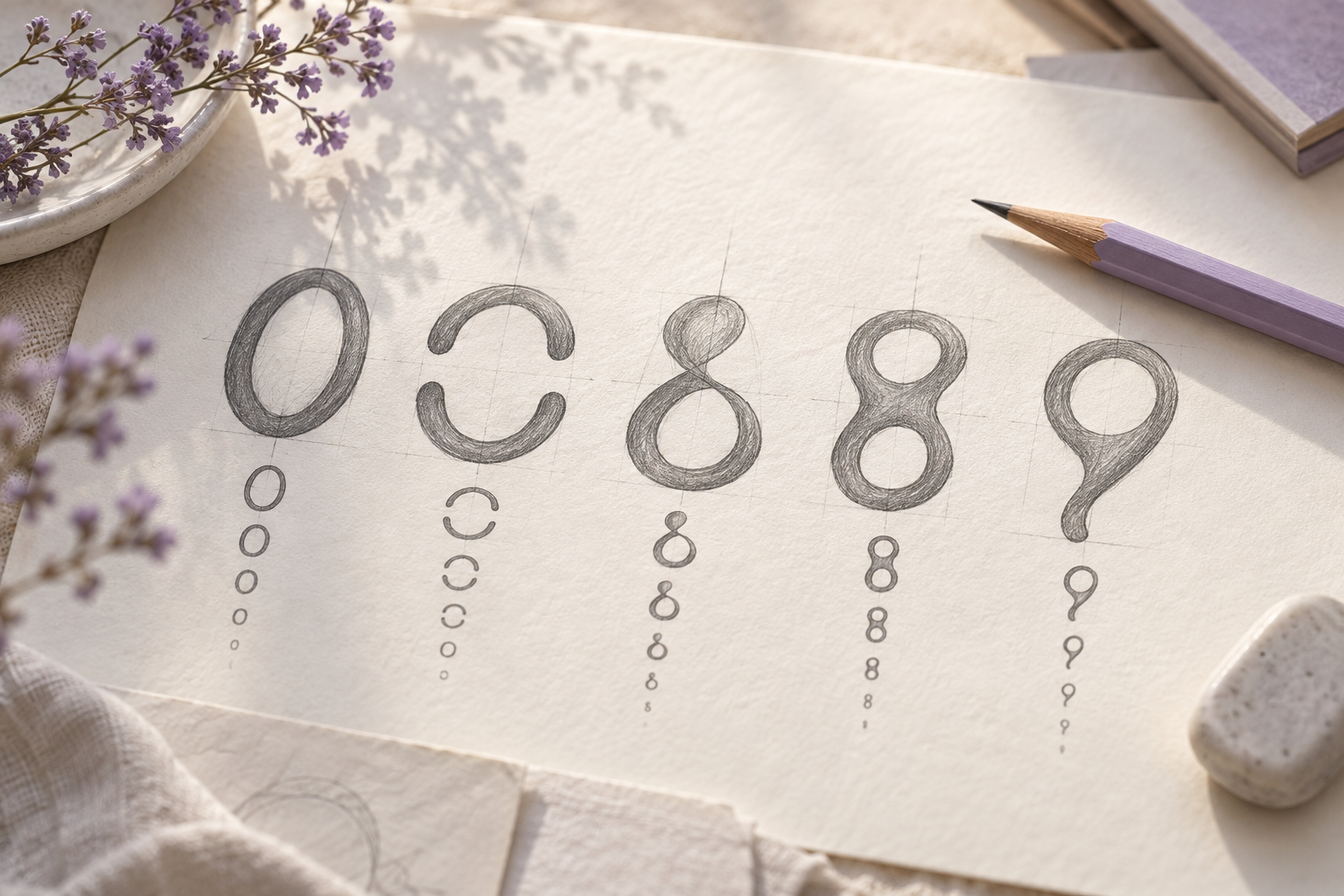
В рукописном шрифте цифры 0, 3, 6, 8 и 9 должны оставаться узнаваемыми не только по отдельности, но и в коротких числовых строках. Для этого каждой цифре задают собственный силуэт, распределяют массу штрихов и сохраняют просветы, которые не исчезают при уменьшении. Ниже — рабочий способ нарисовать спорную группу и проверить её в нужном размере.
Почему именно эти цифры начинают сливаться
В этой группе много округлых контуров и замкнутых или почти замкнутых просветов. У 0 есть одна полость, у 8 — две, у 6 и 9 — по одной, а 3 состоит из двух открытых чаш. Когда почерк превращают в шрифтовые знаки, стилизуют линию и уменьшают изображение, различия между этими конструкциями могут стать слабее: петля 6 закрывается, верх 9 теряет направление, а 3 выглядит как недорисованная 8.
Проблема обычно не в том, что отдельная цифра нарисована плохо. Нечитаемость возникает из-за отношений внутри набора: одинаковой ширины, похожего наклона, схожих соединений или чрезмерно мелких просветов. Поэтому полезно смотреть на группу целиком и сравнивать знаки попарно. Цель — не сделать пять цифр из разных гарнитур, а встроить их в один характерный почерк, оставив каждой устойчивый признак.
Сначала задайте общие правила набора
Перед деталями определите базовую конструкцию: общую высоту цифр, направление наклона, толщину основного штриха и характер округлений. В рукописном начертании линия может слегка колебаться, однако эти параметры должны быть последовательными. Если у 0 овальная вертикальная форма, остальные округлые знаки тоже могут быть немного вытянуты, но их ширина и пропорции не обязаны совпадать с нулём.
Задайте для каждого знака один главный отличительный жест. Ноль может быть узким и спокойным овалом; тройка — открытой справа, с заметно разными верхней и нижней чашами; шестёрка — с петлёй, которая явно возвращается к нижней части; восьмёрка — с двумя различимыми полостями; девятка — с верхней чашей и направленной вниз ножкой. Это не универсальный стандарт рисунка, а система решений, которую нужно согласовать с собственным стилем.
Полезно зафиксировать также минимальный внутренний просвет. Для округлых форм он часто оказывается важнее внешнего контура: слишком маленькая полость в 8 превращается в плотный узел, а узкое раскрытие в 3 теряется при масштабе. Не нужно выводить теоретическое число. Ориентируйтесь на конечное применение: размер ценника, подписи, интерфейсного значения или другого самого мелкого текста, где цифры должны читаться.
Разведите цифры по силуэту и внутреннему пространству
Ноль: одна ровная замкнутая форма
Чтобы 0 не походил на 8, удерживайте в нём одну чистую полость и не добавляйте случайных перегибов, напоминающих перетяжку. Сам знак может быть более узким или округлым — это вопрос характера шрифта. Главное, чтобы внутреннее пространство не сжималось посередине настолько, что глаз начинает видеть две камеры. Если стиль допускает небольшой разрыв или асимметрию, проверьте, не воспринимается ли он как ошибка контура.
Тройка: открытый правый край и разный ритм чаш
У 3 должны читаться две отдельные дуги, открытые в одну сторону. Если обе половины одинаковы и соединены слишком плавно, знак может стать похож на сплюснутую 8. Помогает разница в ритме: например, верхняя дуга компактнее нижней, а центральный изгиб немного смещён. Подберите характерное раскрытие справа и проверьте, что при уменьшении между чашами не возникает ложного замыкания.
Шестёрка и девятка: одна петля, разное направление
В 6 и 9 похожая логика: круглая часть соединяется с продолжающим её штрихом. Их легко различить через направление движения. У 6 хвост или подходящий штрих ведёт взгляд вниз к петле; у 9 верхняя чаша переходит в нисходящую ножку. Не опирайтесь только на то, что один знак похож на перевёрнутый другой: при свободном почерке это сходство может исчезнуть или стать чрезмерным. Наметьте для каждой цифры собственное место соединения и ясную траекторию.
Проверьте положение замыкания: входящий штрих не должен пересекать внутренний просвет или почти касаться противоположной стенки. У 6 оставьте внутри петли достаточно белого поля; у 9 не позволяйте чаше затянуться в узел около перехода к ножке. Если обе цифры имеют одинаковый внешний контур, именно направление хвоста и характер соединения становятся ключом к распознаванию.
Восьмёрка: две полости, но не знак бесконечности
8 часто рисуют как две одинаковые петли, поставленные одна над другой. В живом рукописном стиле симметрия может выглядеть механической, а при маленьком размере две полости сливаются в тяжёлую вертикальную массу. Сделайте соединение читаемым и оставьте между верхней и нижней частями просвет. Они могут различаться размером, но пропорцию стоит выбрать намеренно: например, верхняя камера компактнее, нижняя шире. Так знак приобретает собственный ритм и меньше напоминает ноль с перетяжкой.
Как проверять начертание на малом кегле
Уменьшение — отдельный этап рисунка, а не формальность в конце. Контуры, которые различимы на крупном листе, могут закрыть внутренние пространства при выводе небольшим размером. Проверяйте несколько ступеней масштаба, но обязательно включайте реальный минимальный кегль проекта. Растеризация и качество носителя влияют на результат, поэтому на экране и в печати одна и та же форма иногда воспринимается по-разному.
Соберите короткие последовательности, где соседствуют похожие знаки: 030, 606, 909, 868, 839, 609. Добавьте знакомые сценарии — время, номер страницы, цену, дату или код — без случайных декоративных элементов, которые отвлекают от формы. Попросите другого человека прочитать комбинации, не показывая заранее список. Отмечайте не только ошибочные ответы: пауза, переспрос или неодинаковое чтение несколькими людьми тоже подсказывают, что контраст между знаками недостаточен.
Проверяйте чёрный силуэт и белые просветы по отдельности. На время закройте часть листа и сравните формы пятнами: где у знака центр тяжести, куда направлен выходящий штрих, сколько остаётся пустоты внутри. Затем вернитесь к нормальной строке. Такой переключатель помогает отличить локальную проблему контура от проблемы ритма: отдельная 8 может быть ясной, но выглядеть как утяжелённый знак рядом с более лёгкими 6 и 9.
- Сведите варианты 0, 3, 6, 8 и 9 в один ряд с одинаковой высотой и толщиной линии.
- Посмотрите на формы при размере, который будет самым маленьким в готовом макете.
- Соберите короткие комбинации с повторяющимися и соседними цифрами.
- Проверьте и тёмные штрихи, и светлые внутренние просветы.
- Попросите несколько читателей назвать последовательности, не объясняя им, где возможна ошибка.
- Исправьте только те особенности, которые мешают чтению, затем повторите проверку в строке.
Типичные ошибки при рисовании цифр
- Делать все знаки одинаково узкими ради аккуратной колонки. Ровное выравнивание не должно стирать индивидуальный силуэт.
- Уменьшать штрихи без проверки внутренних просветов. Замкнутая форма может стать пятном даже при аккуратном внешнем контуре.
- Делать верхнюю и нижнюю части 3 или 8 совершенно одинаковыми. Ритмическая разница нередко помогает быстрее распознать цифру.
- Полагаться на одну изолированную цифру на большом масштабе. Читатель встречает знак в строке, где соседние формы меняют восприятие.
- Исправлять почерк случайными украшениями. Дополнительная засечка или надлом полезны только тогда, когда органично входят в систему и остаются заметны на малом размере.
- Проверять только глазами автора. Привычка к собственному рисунку мешает заметить неоднозначность, которую видит новый читатель.
Короткий чеклист перед завершением набора
- У каждой цифры есть один устойчивый отличительный признак.
- Ноль сохраняет одну полость, а восьмёрка — две.
- У тройки видны раскрытие справа и две чаши.
- У шестерки и девятки ясно направление штриха и место соединения.
- Просветы остаются открытыми в самом маленьком размере применения.
- Цифры читаются в последовательностях, ценах, датах и других коротких строках.
- Другой человек может прочитать пробный набор без предварительной подсказки.
Для рукописного шрифта отдельно решите, нужно ли сохранять естественное различие повторных написаний. Если источник — живой почерк, у цифр могут быть небольшие отклонения, но базовая конструкция должна оставаться узнаваемой: не превращайте одну из версий 6 в почти закрытую 8 или один из вариантов 3 в знак с новым соединением. При переносе образцов в цифровой набор полезно сравнить исходный рисунок с итоговым отображением, чтобы сглаживание линии не стёрло характерные места раскрытия. Запишите выбранные правила для спорных знаков и применяйте их ко всем числам. Это особенно помогает, если форму позже будут расширять или корректировать: следующий этап сможет сохранить не только настроение рукописи, но и согласованность цифр.
Нужно ли делать цифры одинаковой ширины?
Нет. Одинаковая ширина полезна в таблицах и кодах, но не является обязательным правилом для каждого рукописного начертания. Сначала сохраните узнаваемый силуэт и общий ритм, затем решите, нужна ли проекту ровная колонка цифр.
Как отличить 0 от 8 в маленьком размере?
Сохраните у нуля одну незажатую полость, а у восьмёрки — два ясных просвета, разделённых заметным соединением. Проверяйте эти пространства в целевом размере: если они закрываются, меняйте внутренний контур или толщину штриха.
Чем надёжнее различить 6 и 9?
Задайте для каждой цифры отдельное направление перехода между чашей и хвостом: у 6 движение ведёт к нижней петле, у 9 — от верхней чаши вниз. Затем сравните знаки рядом и проверьте, не делает ли стиль их простыми перевёрнутыми копиями.
Можно ли сохранить неровность рукописной линии?
Да, характерная неровность поддерживает авторский стиль, если не закрывает просветы и не разрушает ключевые переходы. Оставьте вариативность в толщине или небольших изгибах, но стабилизируйте те части контура, по которым читатель отличает цифры.
Какие числа использовать для пробной строки?
Составьте короткие комбинации, в которых цифры из спорной группы стоят рядом или повторяются, например 030, 606, 909 и 868. Добавьте значения из реального макета — дату, цену или номер. Так проверка покажет и форму каждого знака, и его поведение среди соседей.
Нужно ли проверять цифры на бумаге, если шрифт будет цифровым?
Если цифры появятся в печати, проверьте хотя бы один отпечатанный образец на целевом размере. На бумаге фактура и способ воспроизведения могут иначе показать тонкие штрихи и узкие полости. Для экранного применения отдельно смотрите реальное отображение на устройстве.
Читаемая группа 0, 3, 6, 8 и 9 строится на разных силуэтах, ясных внутренних пространствах и проверке в настоящем размере. Не обязательно отказываться от выразительного почерка — достаточно определить для каждой цифры устойчивый жест и убедиться, что он остаётся видимым в строке. Создайте собственный шрифт на fontgenerator.ru, затем проверьте его на числах, которые встретятся читателю в работе.